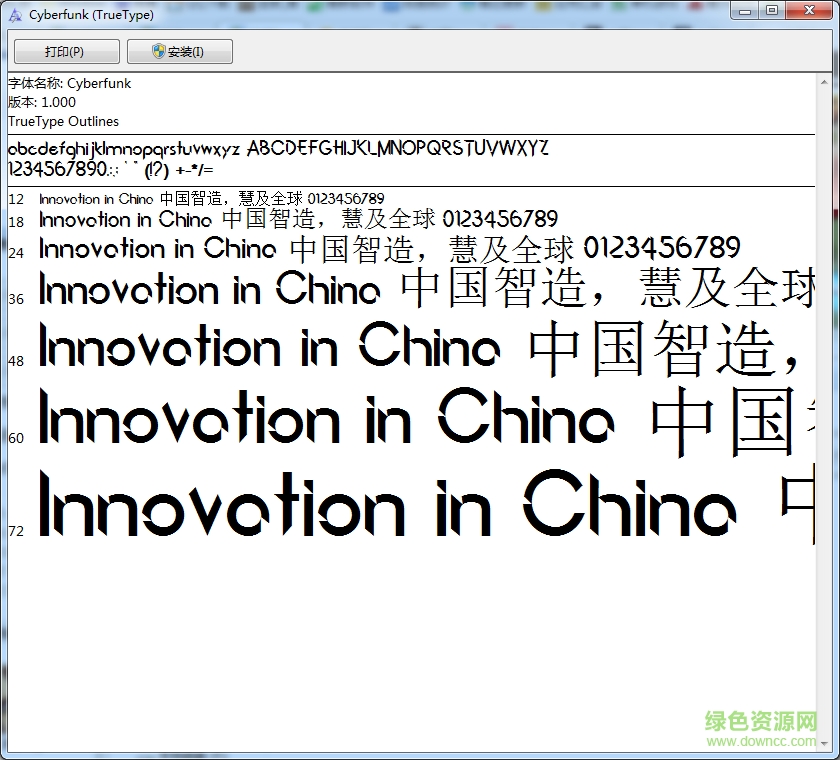
CYBERFUNK字體
CYBERFUNK是一款簡約大方的英文字體,字體圓潤線條靈動彰顯個性,使用領(lǐng)域廣泛,一鍵安裝便可輕松使用??靵砭G色資源網(wǎng)下載體驗吧!
CYBERFUNK字體介紹
CYBERFUNK字體是一款好看的英文字體,字型比較隨意,比一般電腦設(shè)計出來的無襯線字體更加生動有趣。